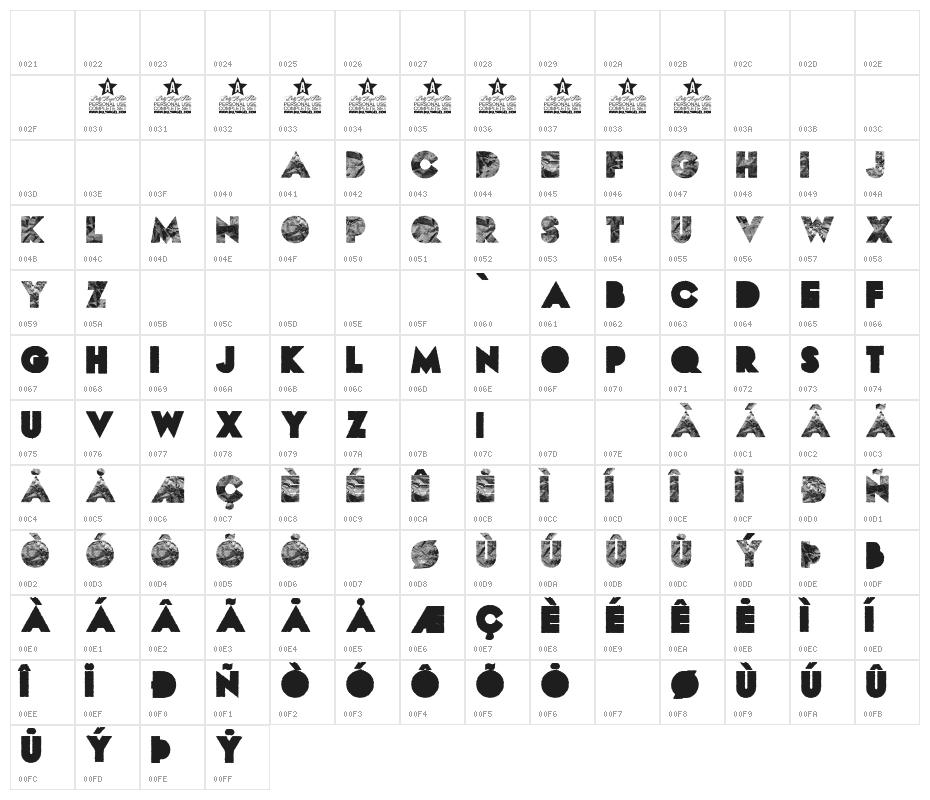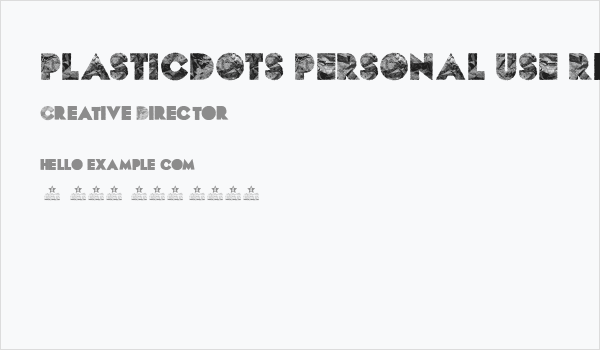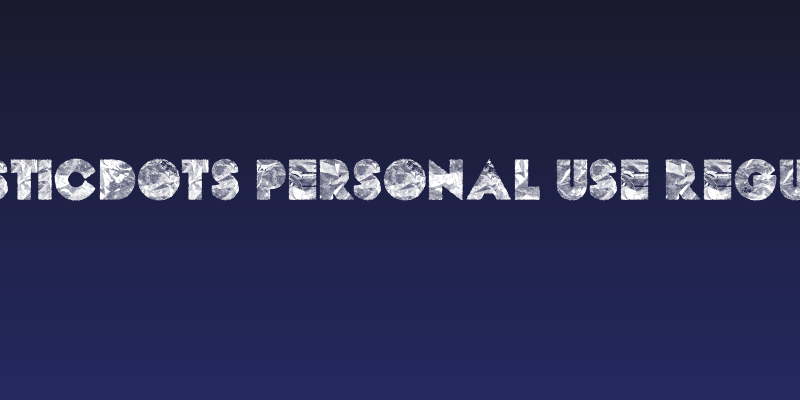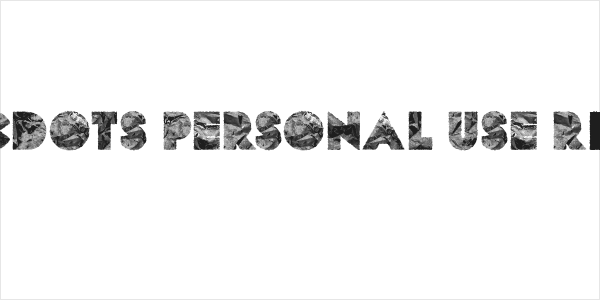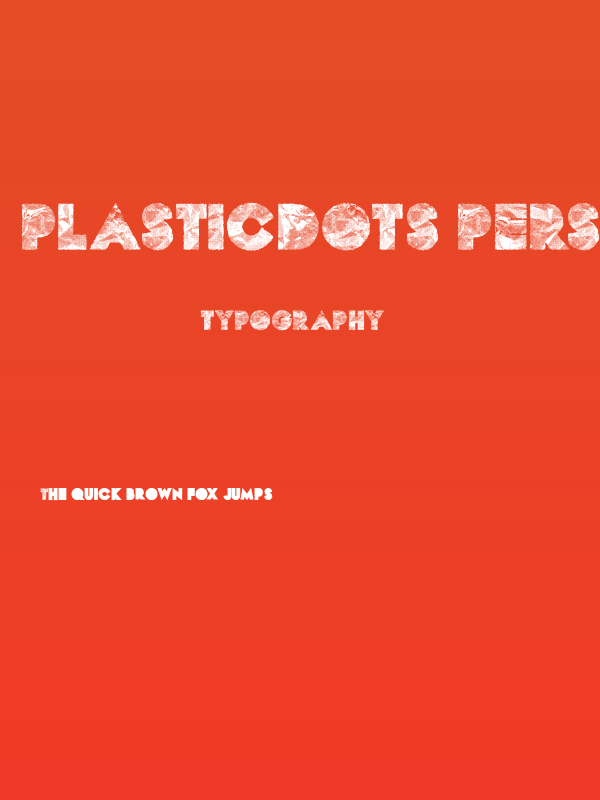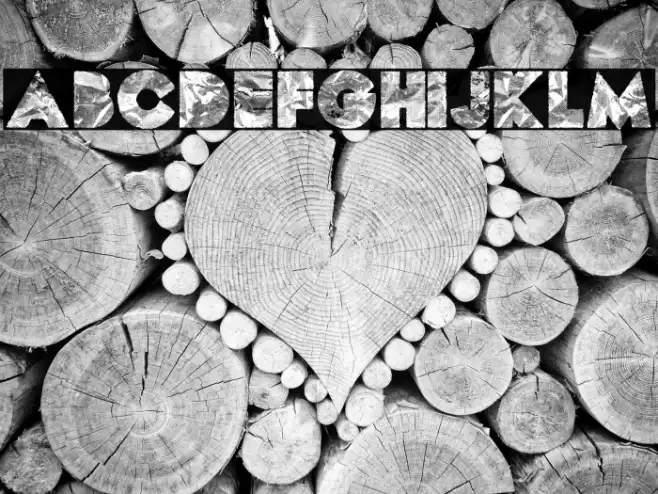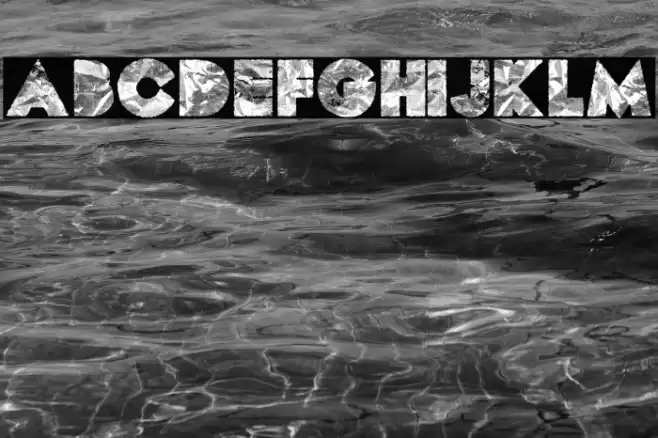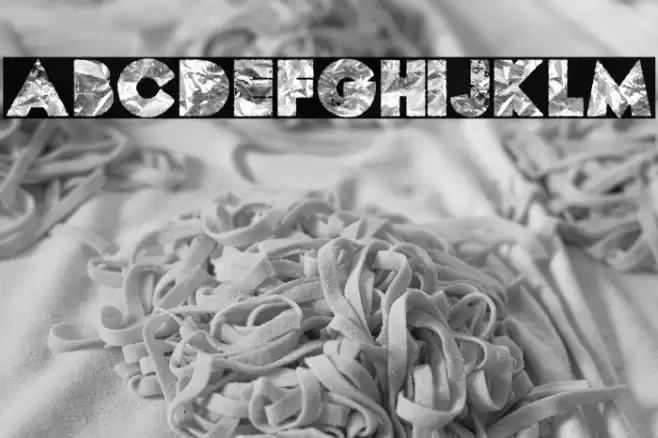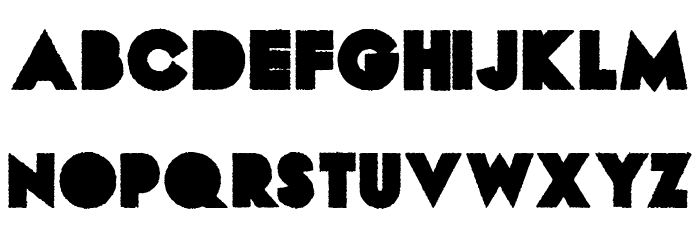
PLASTICDOTS PERSONAL USE Regular Font
| Stile generale | Modern, Artistic |
| Progetti proposti | Ideal for posters, album covers, branding projects, and any design requiring a bold statement. |